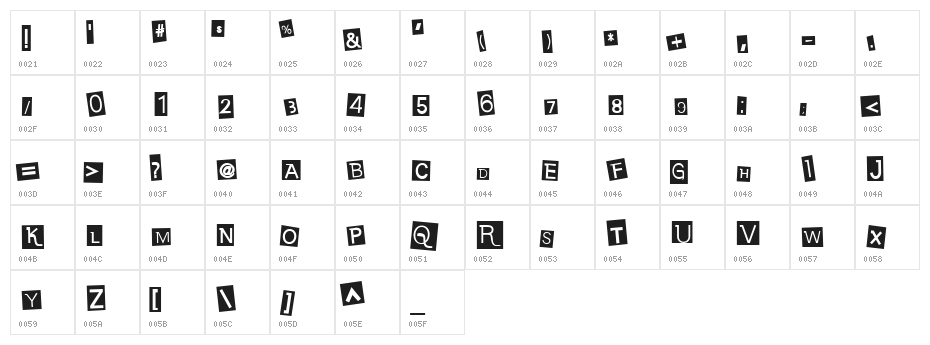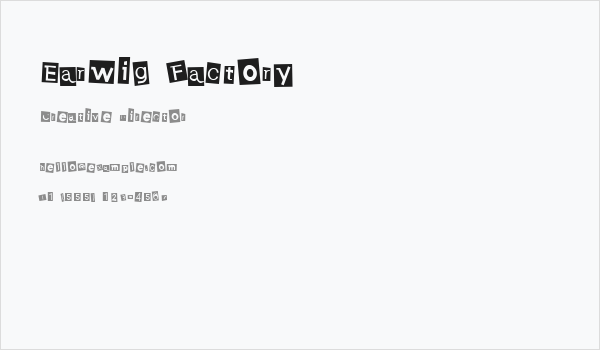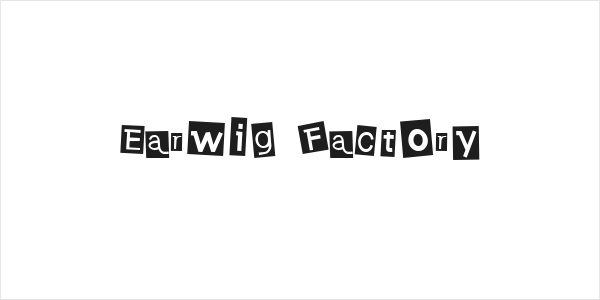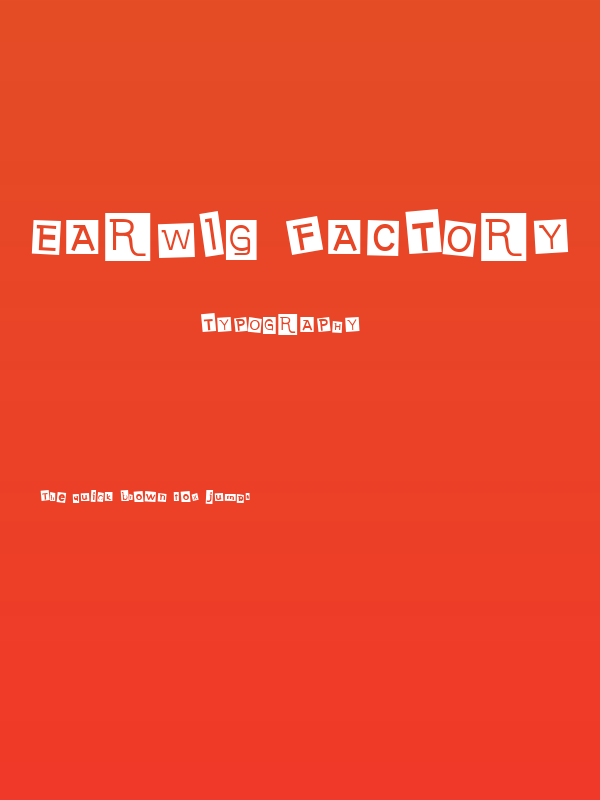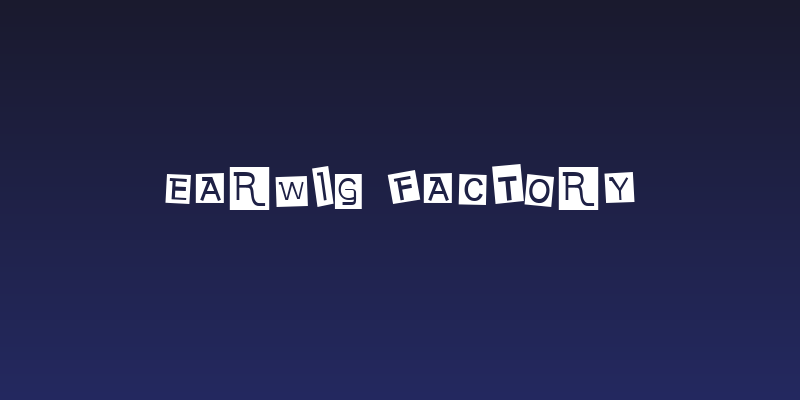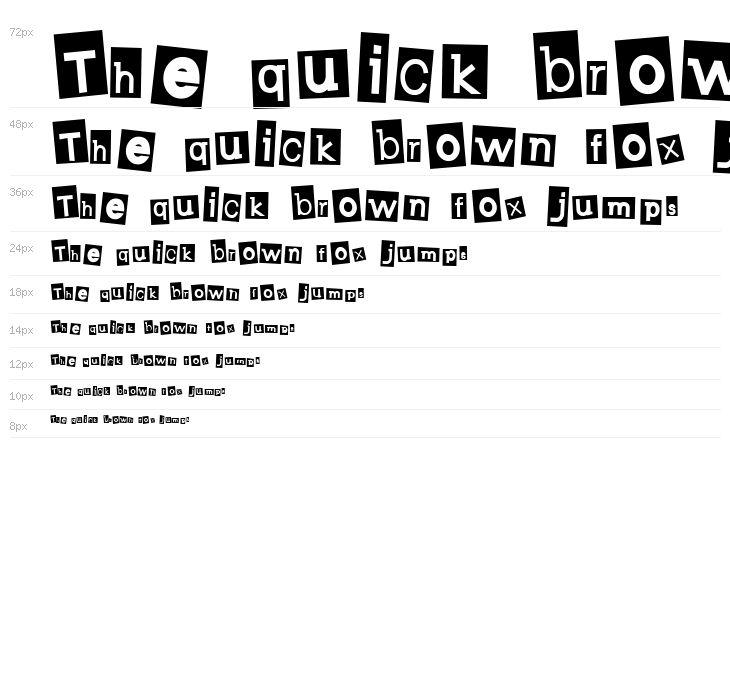
Earwig Factory Font
| Категория | Decorative |
| Область применения | Headlines, Posters, Artistic Designs |
| Рекомендуемые проекты | Ideal for creative projects such as posters, album covers, or any design requiring a bold, artistic statement. |